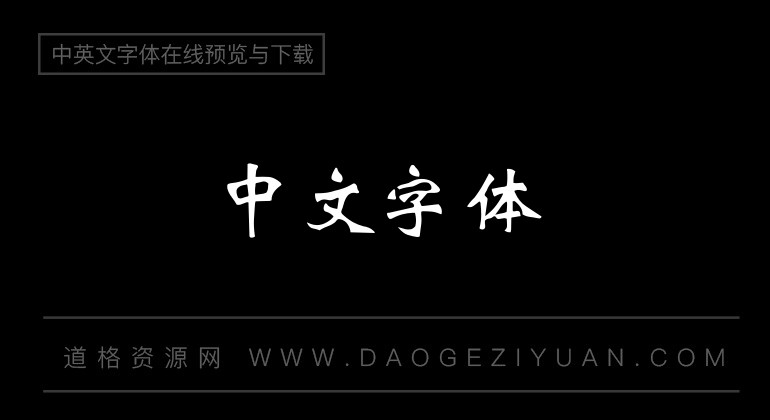
汉鼎简魏碑
汉鼎简魏碑是一种繁体字体,它来源于中国古代的魏碑,汉鼎简魏碑以魏碑的结构为基础,根据现代排版原则精心设计而成。它具有清晰的结构、清晰的笔画、清晰的字形,以及精致的细节,给人以深刻的印象。汉鼎简魏碑适用于中文排版,比如书籍、文章、宣传单等。
汉鼎简魏碑是一款非常不错的手写艺术字体,具有很好的视觉感,适合于文化类的宣传设计、商业类品牌的广告和产品包装设计以及个性化文字排版等较多场景。